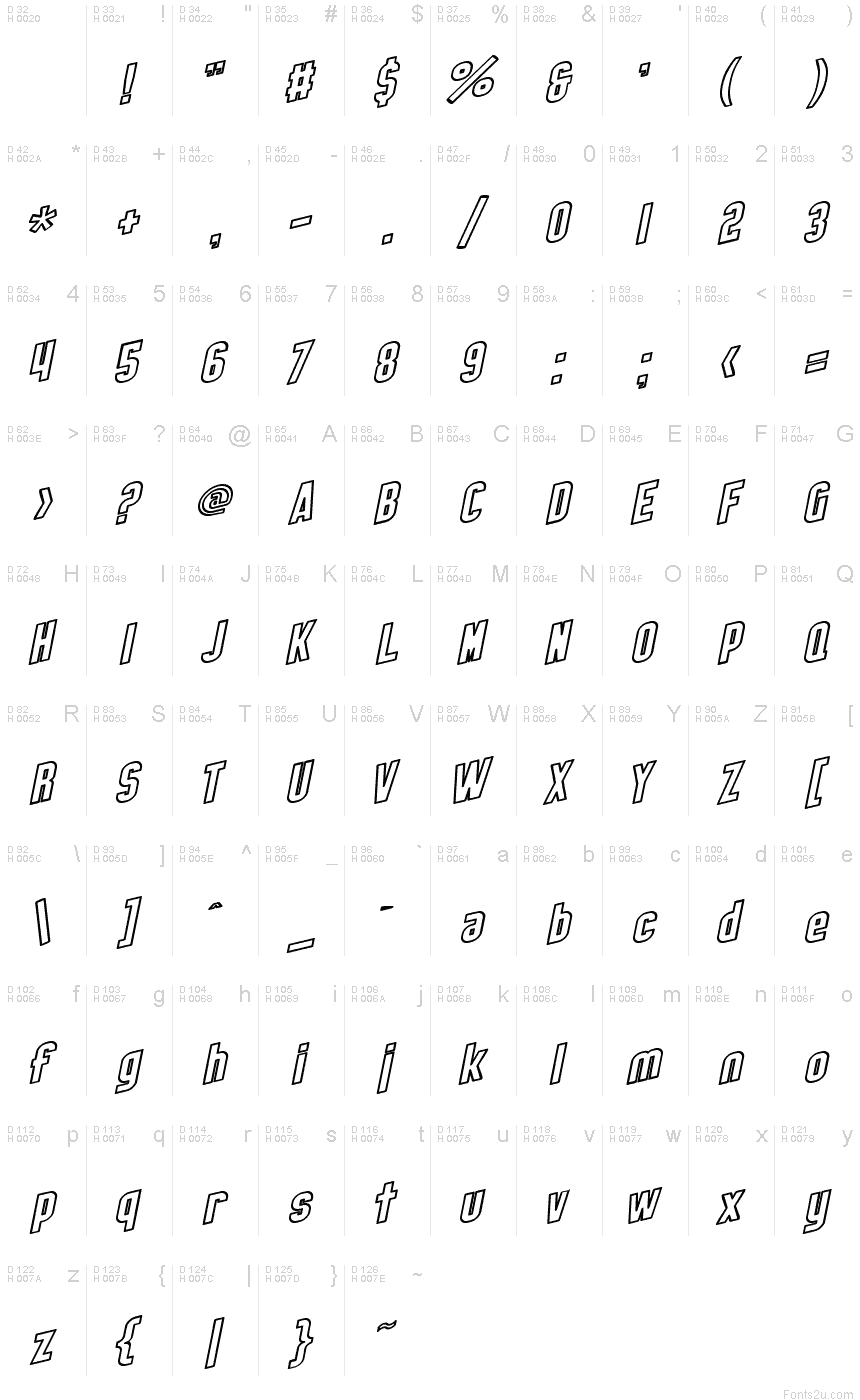
SF Obliquities Outline od ShyFoundry to nowoczesny, darmowy font typu display, wyróżniający się konturowym krojem, ostro pochylonymi wielkimi literami i energią w stylu komiksowym. Litery wyglądają, jakby zostały nakreślone grubym mazakiem – są surowe, kanciaste i lekko wychylone do przodu. Całość przypomina klimatem napisy z gier arcade w stylu retro oraz sportowe nagłówki.
Font naturalnie sprawdzi się na plakatach, w grafikach do gier, zinach, planszach tytułowych i okładkach, gdzie dynamika liczy się bardziej niż wygładzone wykończenie. Jako darmowy krój, świetnie nadaje się również do logotypów, monogramów i krótkich haseł brandingowych – otwarte kontury sprawiają, że wielkie litery wydają się lekkie, a smukły, poszarpany rytm nadaje nawet prostym inicjałom naładowanego, animowanego charakteru.
SF Obliquities Outline
ShyFoundry
Derek Vogelpohl